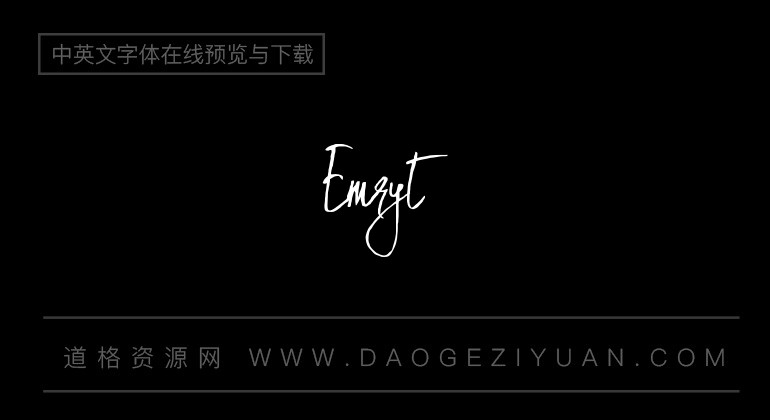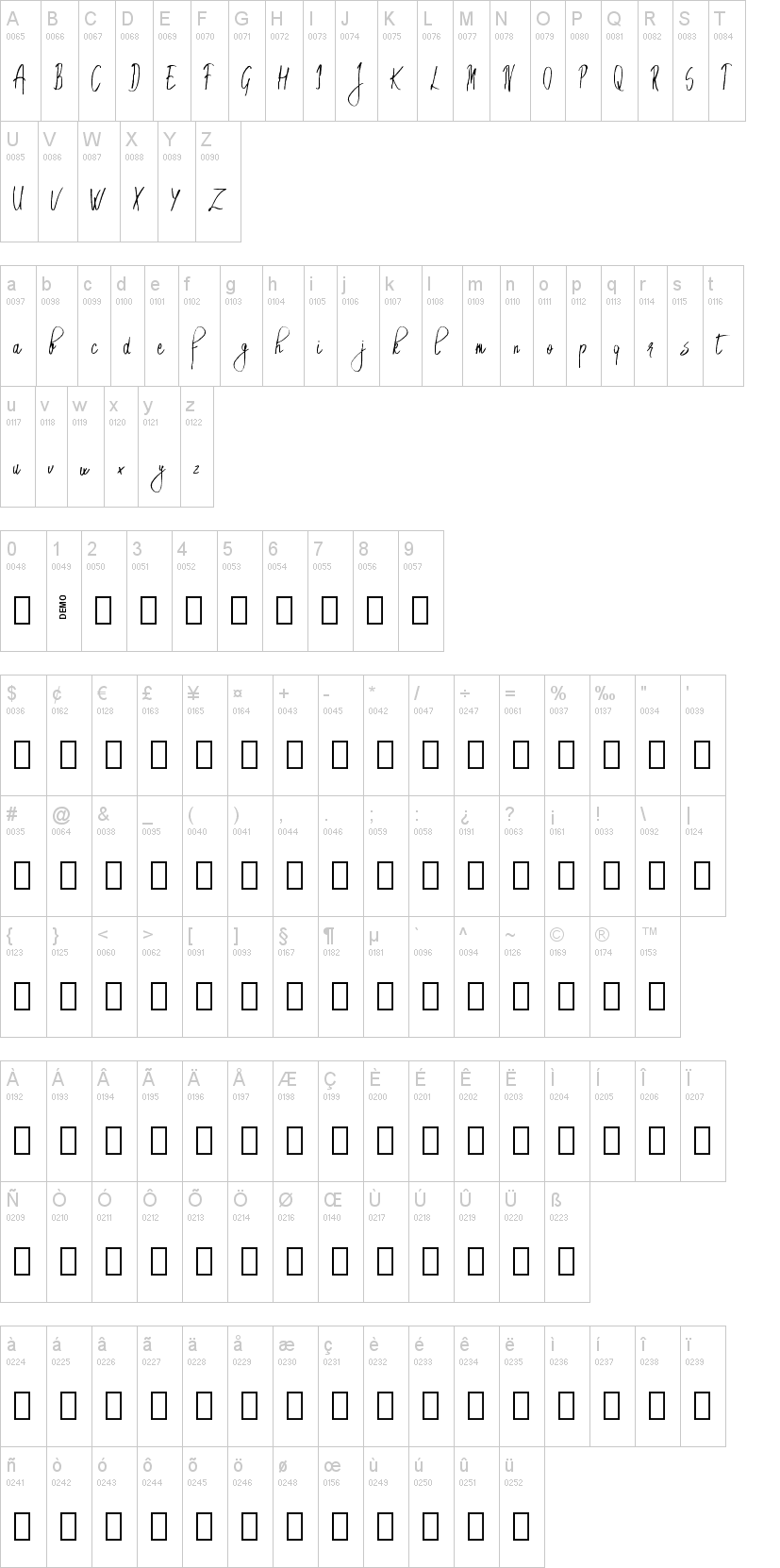
Emryt 字体是一款简洁、明快、优雅的多功能字体,适用于各种印刷和屏幕媒体。它具有良好的可读性和较高的可视性,可以为你的设计创造出清晰、精致的效果。它还拥有完整的字母、数字和符号,可以满足你的多种文本需求。内容介绍
Emryt是一款非常不错的手写艺术字体,具有很好的视觉感,适合于文化类的宣传设计、商业类品牌的广告和产品包装设计以及个性化文字排版等较多场景。